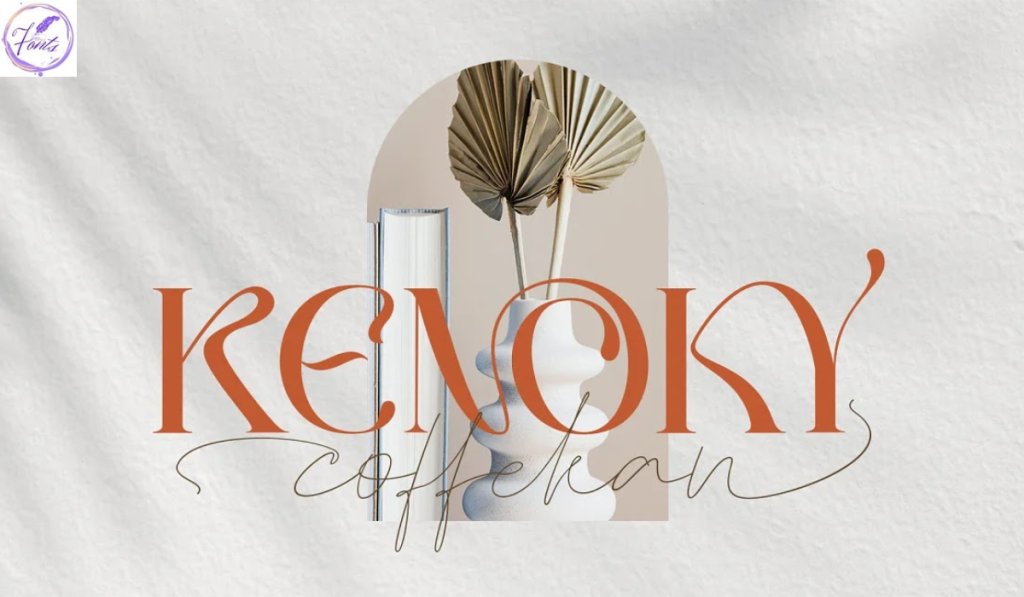
Font Kenoky Coffekan việt hóa
Tác giả: Alit Suarnegara
Ngày phát hành: 2021
Ngôn ngữ: Tiếng Việt, Tiếng Anh, và nhiều ngôn ngữ khác
Bộ Font: Kenoky Coffekan
Phân loại: Cá tính, độc đáo
Kiểu chữ: Serif, Script
Độ dày: Thin, Light, Regular, Bold
Font Kenoky Coffekan là một phông chữ độc đáo và sáng tạo, được thiết kế bởi Alit Suarnegara và ra mắt vào năm 2021. Phông chữ này mang đến sự kết hợp hoàn hảo giữa nét cổ điển và hiện đại, tạo nên một phong cách riêng biệt và đầy cuốn hút. Font Kenoky Coffekan thích hợp cho các thiết kế logo, tiêu đề, và các dự án sáng tạo cần sự nổi bật và ấn tượng. Phiên bản việt hóa của font này đã được tinh chỉnh kỹ lưỡng, đảm bảo các ký tự tiếng Việt hiển thị rõ ràng và đẹp mắt, mang lại trải nghiệm sử dụng tối ưu cho người dùng.
Đánh giá font Kenoky Coffekan
Font Kenoky Coffekan được đánh giá cao bởi sự linh hoạt và thẩm mỹ trong thiết kế. Các ký tự của phông chữ này được thiết kế tỉ mỉ, tạo nên sự hài hòa và dễ đọc. Nhiều nhà thiết kế đã sử dụng font Kenoky Coffekan trong các dự án của họ và nhận thấy rằng nó giúp tăng tính thẩm mỹ và sự chuyên nghiệp cho sản phẩm. Sự việt hóa của font này cũng được thực hiện rất tốt, đảm bảo rằng các ký tự tiếng Việt không chỉ đẹp mà còn phù hợp với ngữ cảnh sử dụng, mang lại cảm giác tự nhiên và mượt mà cho người dùng.